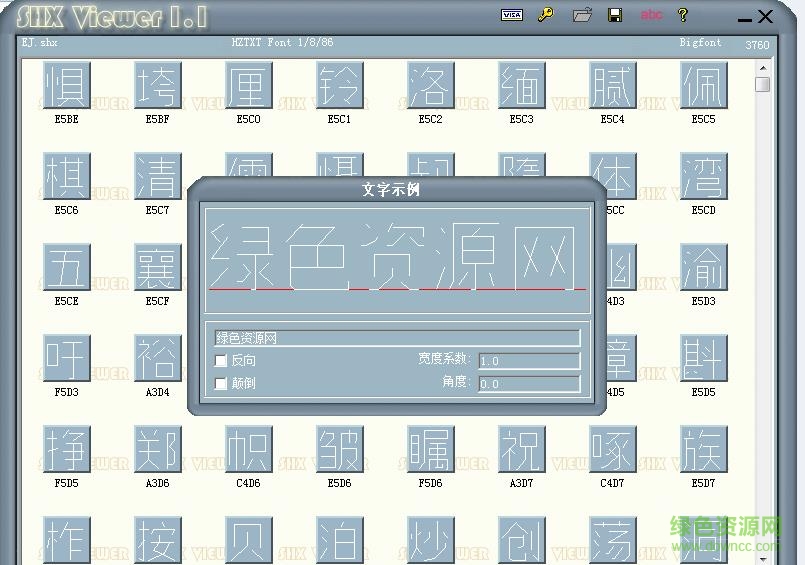
ej.shx
ej.shx字體文件是在cad制圖以及看圖過程中需要使用的字體,當(dāng)用戶在遇到很多cad圖紙打不開的情況,同時(shí)提醒你缺失某某字體時(shí)即需要下載字體文件安裝才能夠打開圖像!
ej.shx字體的風(fēng)格獨(dú)具風(fēng)味,通過在視圖中添加此款字體文字將能夠獲得注釋的效果,同時(shí)也支持制圖過程中的眾多專業(yè)符號(hào)以及圖案的輸入,用途廣泛!
ej.shx字體字體介紹